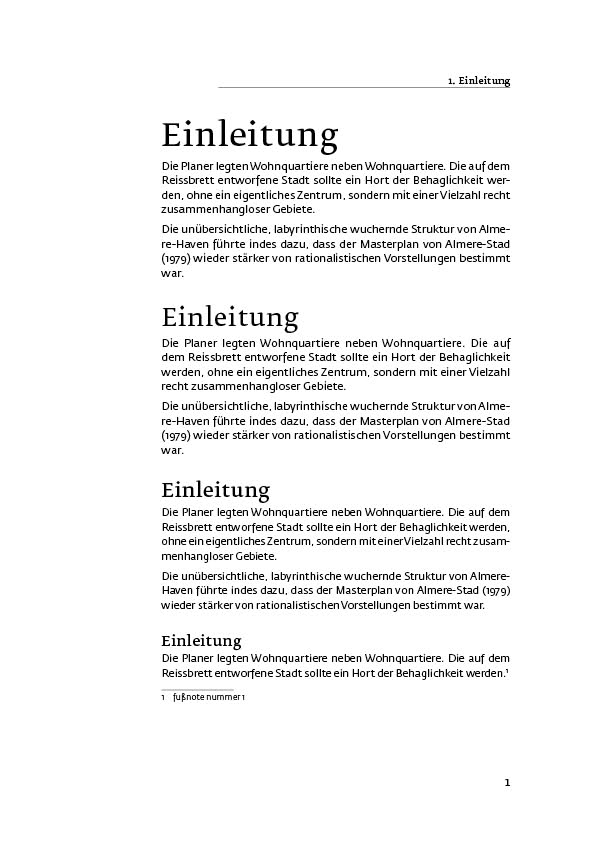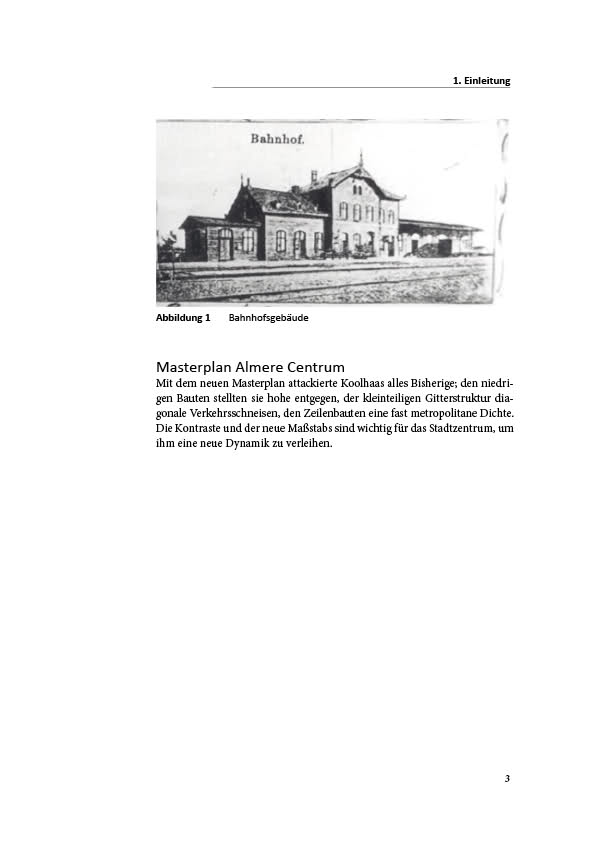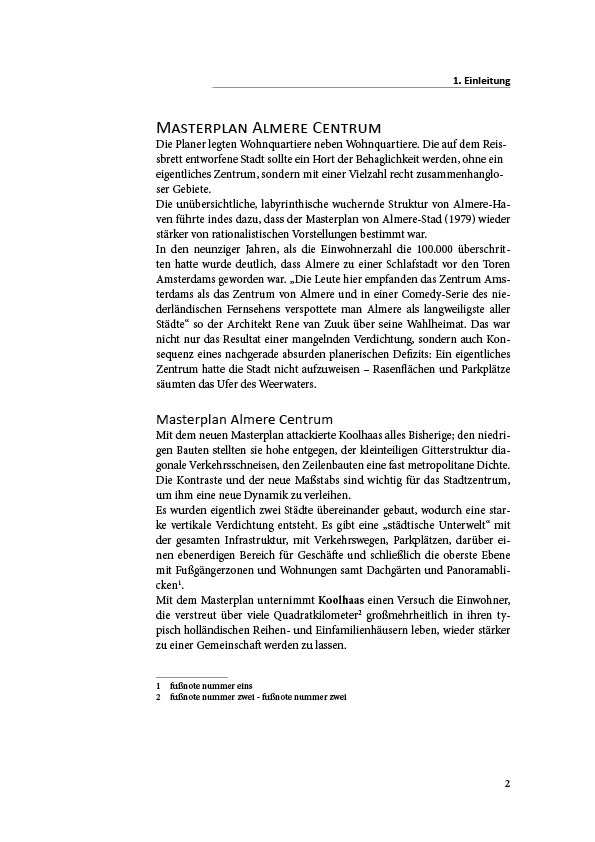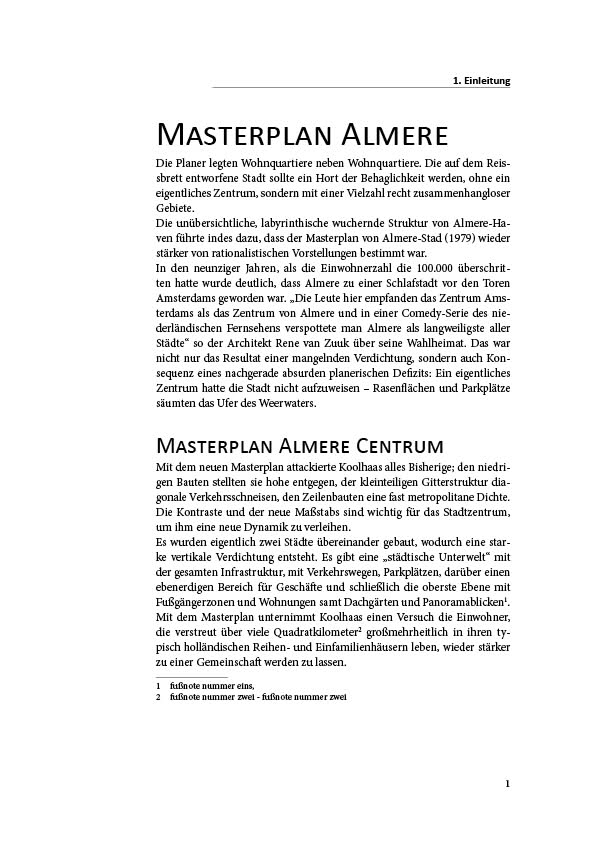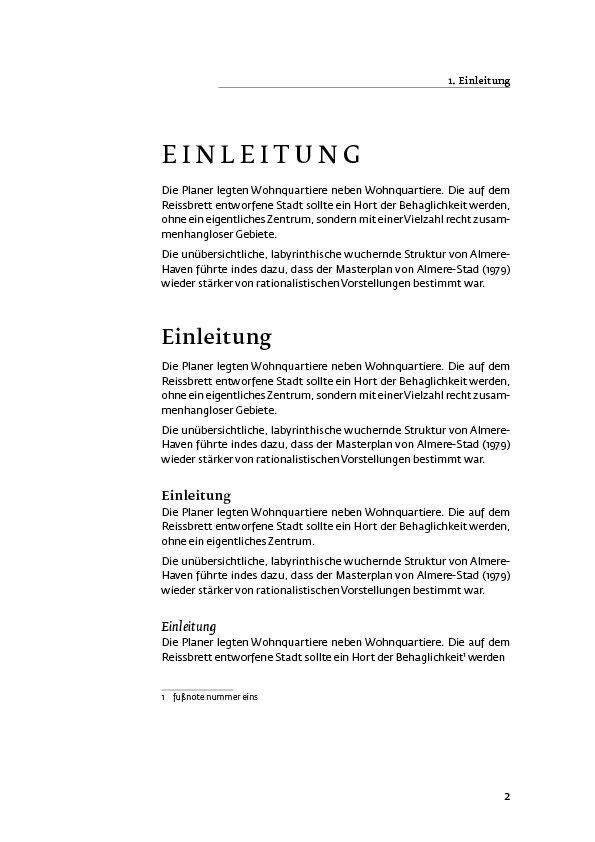
Gestaltung meiner Masterthesis
ich schreibe nächstes semester meine masterthesis im bereich architektur über die entwicklung und die wertermittlung von bahnhöfen. ich habe mich etwas durchs forum gearbeitet und einiges davon umgesetzt. mein layout sieht jetzt mal so aus, was kann ich noch verbessern?
überschriften (4 ebenen), bildunterschriften, titel: calibri
fliesstext, seitenzahlen, fußnoten: minion pro
(können auch andere sein, wenn jemand was schönes einfällt.)
seitenränder:
- oben: 2,7 cm
- unten: 5,0 cm
- links: 5,5 cm (- 1,0 cm für die bindung)
- rechts: 3,0 cm
mit diesen einstellungen komme ich auf 67-70 zeichen pro zeile...
die arbeit soll am ende gebunden und 1-seitig gedruckt werden.
Bevor die Profis fundiert rangehen, zwei/drei kurze Gedanken vom interessierten Laien:
* Die Calibri ist für den Bildschirm optimiert und kommt in Textgrößen auch gedruckt ganz ordentlich. In Headlinegrößen find ich sie drittklassig und neben der Minion wär sie mir einfach zu ordinär. Und für Kapitälchen solltest du auch eine Schrift verwenden für die die als eigenständiger Schnitt vorliegen. Bei deiner Schriftprobe fällt mir auch auf, dass die Headline ganz übel, besser gesagt gar nicht ausgeglichen ist.
* Für den Bereich Architektur wär mir die Minion zu lyrisch, da könnte was progressiveres, stylischeres ran. Vor 20 Jahren hätten wohl viele nach der Rotis gerufen :huhu:
* In deiner Textprobe sind ganz hässliche Trennungen am Zeilenende. Darüber hinaus ist der rechte Rand sehr sehr unruhig.
* Den Seitenspiegel empfinde ich als recht angenehm.
danke schonmal für deine meinung...habe gerade mal kurz die rotis angeschaut/probiert. sie gefällt mir sehr gut!
noch andere schrift vorschläge?
Und für Kapitälchen solltest du auch eine Schrift verwenden für die die als eigenständiger Schnitt vorliegen.
Und überhaupt halte ich Kapitälchen an vielen Stellen, wo sie eingesetzt werden, für verfehlt und, und so auch hier: Die Überschriftenbänder wirken viel ruhiger, wenn man sie gleich richtig in Versalien setzt.
und warum überhaupt die Großbuchstaben? Mir würde Groß- und Kleinschreibung in den Überschriften reichen.
setzen/schreiben werde ich das ganze, wie auch schon bei den musterseiten gemacht, mit InDesign.
ohne hier die üblichen Relfexdiskussionen zur Rotis anstoßen zu wollen: Es gibt viele Leute, die die Rotis im Fließtext nicht lange lesen können.
dies habe ich auch schon gelesen und daher mal was ausgedruckt. ich finde man kann es noch gut lesen.
welche schriftart für die überschriften würdet ihr mir dann zur rotis empfehlen?
und welche rotis soll ich nehmen?
semi sans = gefällt mir besser, da stylischer
serif = bessere lessbarkeit
oder gleich die semi serif, da von beiden punkten etwas??
Ich denke, Steff11 wollte nicht sagen „nimm Rotis“, sondern „nimm was stilistisch passendes“.
Wenn man es „noch gut lesen“ kann, ist das doch ein Grund, stattdessen eine Schrift zu nehmen die man besonders gut lesen kann und eben auch stilistisch passt. Da du dich mit Bahnhöfen beschäftigst, wäre doch vielleicht eine Leitsystemschrift („Zu den Gleisen“) was. Oder eine mit industrieller Anmutung.
kannst du mir auch ein paar beispiele dazu geben? danke!
Das mit besonders guter Lesbarkeit in 11pt-Fließtexten zu vereinbaren, dürfte doch recht schwierig sein. Leitsystemschriften sind doch für einen ganz anderen Einsatz konzipiert und "industriell anmutend" wie etwa die DIN ist auch nicht der ganz große Bringer ... nicht umsonst wird Belletristik über weite Strecken in humanistischen Antiquas gesetzt, oder?
Ich denk im Moment vielleicht eher an die Fedra Serif
vielen dank für deinen ausführlichen beitrag. ich habe mal versucht deine anregungen umzusetzen...ich hoffe es ist was geworden!
p.s.: gedruckt bzw. in guter auflösung sind die abstufungen noch besser zu sehen...
absatz abstand habe ich größer gemacht!
Wird eigentlich nur einseitig gedruckt oder auf Vorder- und Rückseite? In letzteren Fall solltest Du berücksichtigen, dass die Rückseiten durchscheinen können, was sich bei fehlender Registerhaltigkeit störend bemerkbar macht.